文字是人类文化的重要组成部分,无论是在何种视觉媒体中都是重要的因素。做为标题文字的的字体的适合与否影响的是最直观的视觉传达效果。一款合适设计标题风格的字体可以增强视觉传达效果,提高作品的诉求。作为标题设计的字体一定要具备张力、创意吸引力和端庄大气的特征,接下来和小编一起看看下面图片字体这些集“智慧与美貌”于一身的字体吧!
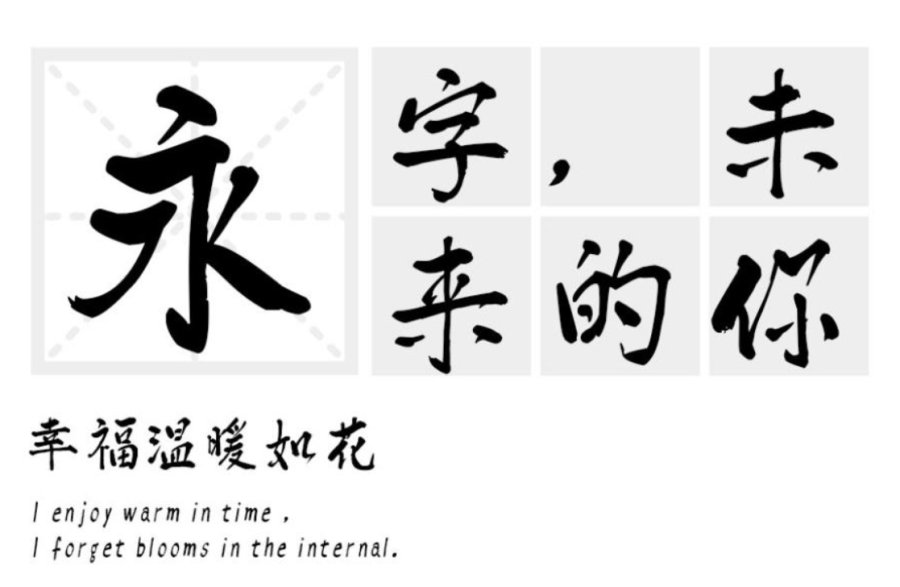
汉标清新洒脱体:这款字体运笔舒展飘逸,部件排列别具一格,韵味缠绵,恍如初见心动一刻,呼之欲出的雀跃感受。字体造型富于力度,简洁爽朗,现代感强, 有很强的视觉冲击力作为标题字体有画龙点睛之效。
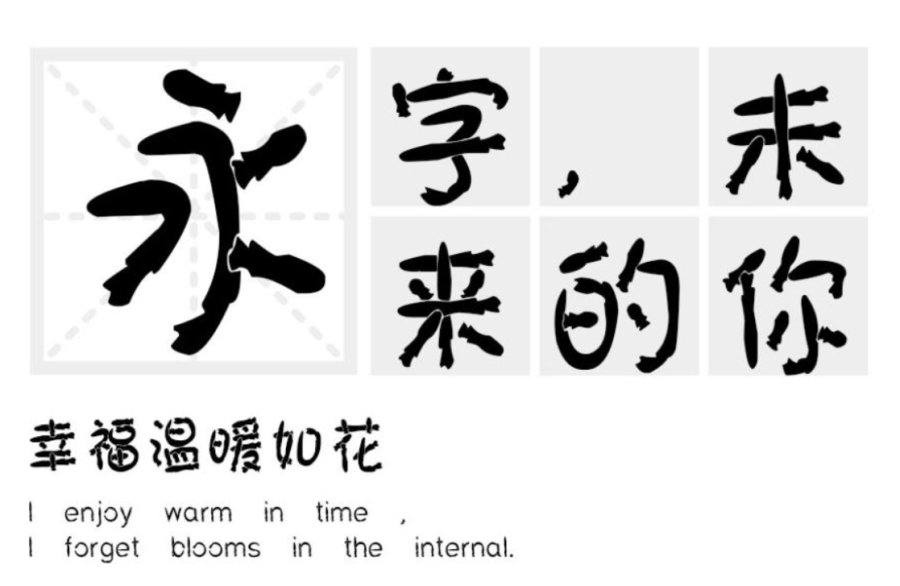
汉标鬼符体:这款字体笔画运用了鬼符图形元素来构建,把这些笔画做成了鬼符,概括为飘逸的鬼符,并且使左右舒展的笔画尽量对称,最大限度地简化笔画鬼符造型。字体的造型奇妙,不同一般,个性非常突出,给人的印象独特而新颖,令人过目难忘,用于现代感、时尚主题的标题字体最为合适。
汉标高光毛笔:这是一款书法味道的纯手写字体,作者运用大号毛笔精心书写,楷书味道浓厚,由于字体较大,使得笔画清晰度较高易于看图片识别字体,笔画中也减少了过多的处理和笔势,厚重、饱满。字体整体造型规整,具有重量感,庄严雄伟,不可动摇,适用于正式性、艺术性的主题。